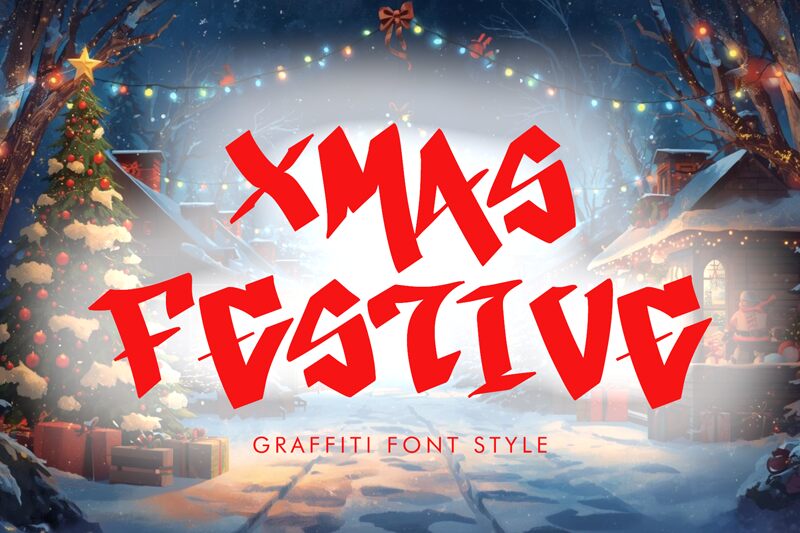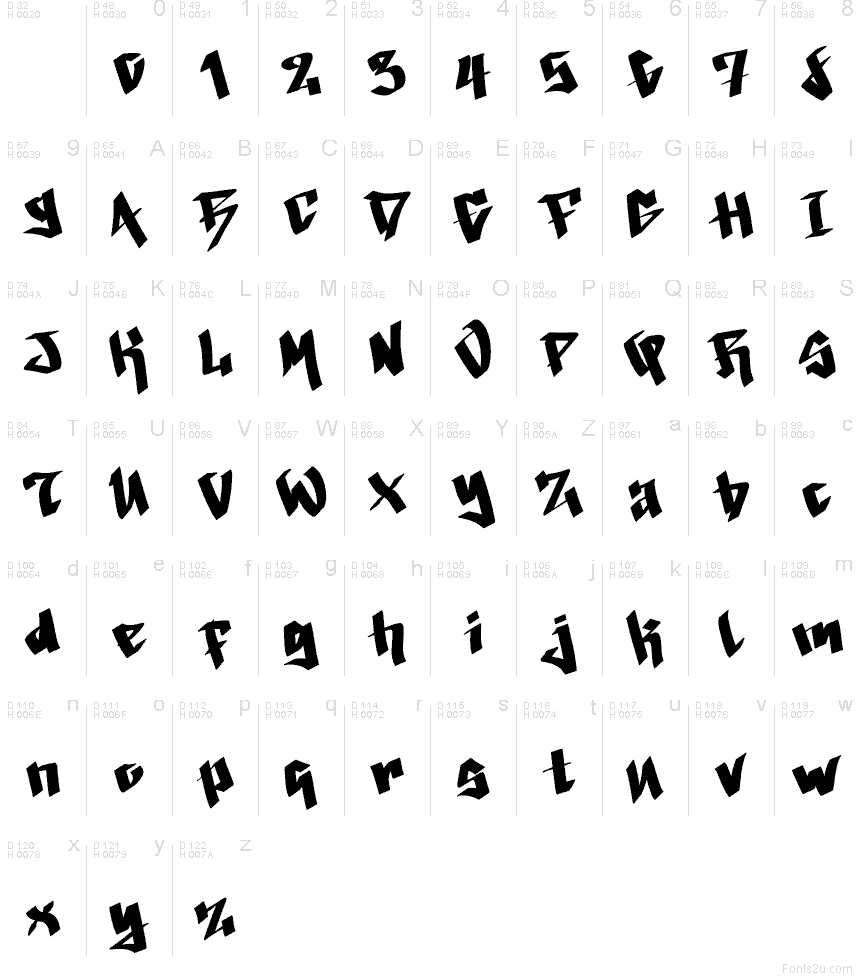
Xmas Festive ist eine kostenlose Graffiti-Schrift mit scharfen, kantigen Strichen, geneigten Formen und ausgeschnittenen Kanten, die den Buchstaben einen Look wie frisch gesprüht verleihen. Der weihnachtliche Name passt perfekt zu den energiegeladenen Formen, die eher handgezeichnet als geometrisch wirken und durch spitze Verbindungen und unregelmäßige Ecken überzeugen.
Xmas Festive eignet sich hervorragend für Festtags-Poster, Party-Flyer, Streetwear-Designs, Musik-Cover und Social-Media-Banner, bei denen ein rauer, ausdrucksstarker Titel gefragt ist. Dank der gezackten Formen, die einen starken grafischen Rhythmus mitbringen, ist diese Schrift auch ideal für Sticker und Logo-Akzente.